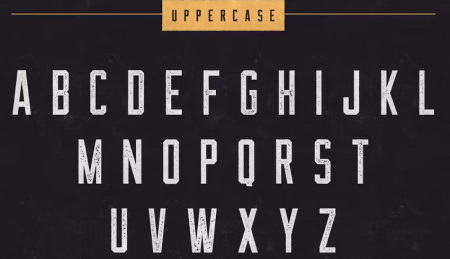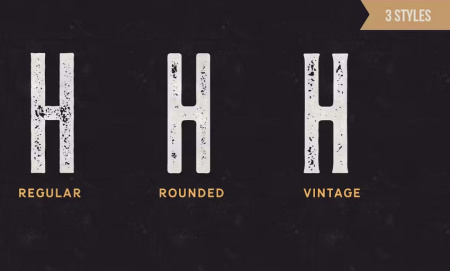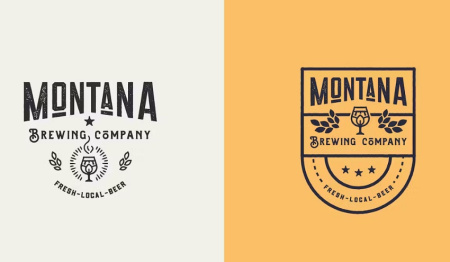
فونت رایگان انگلیسی The Farmer
فونت انگلیسی رایگان The Farmer
فونت رایگان انگلیسی The Farmer که شامل 3 سبک است: معمولی، گرد و نسخه های قدیمی. این یک فونت انگلیسی با حروف بزرگ All-Caps است که هر نسخه شامل یک بافت (Aged) و جایگزین است. با 3 سبک و جایگزین های نمادین، The Farmer می تواند مجموعه ای متنوع از زیبایی شناسی را ارائه دهد. برای دانلود رایگان این فونت از جی اف ایکس دانلود در ادامه مطلب با ما همراه باشید.
✅ نام فونت: The Farmer
✅ عدد، نقطه گذاری و نماد
✅ جایگزین های سبک
✅ 3 سبک: منظم، گرد، قدیمی